和風デザインにぴったりな毛筆フリーフォント23選【無料・商用可】
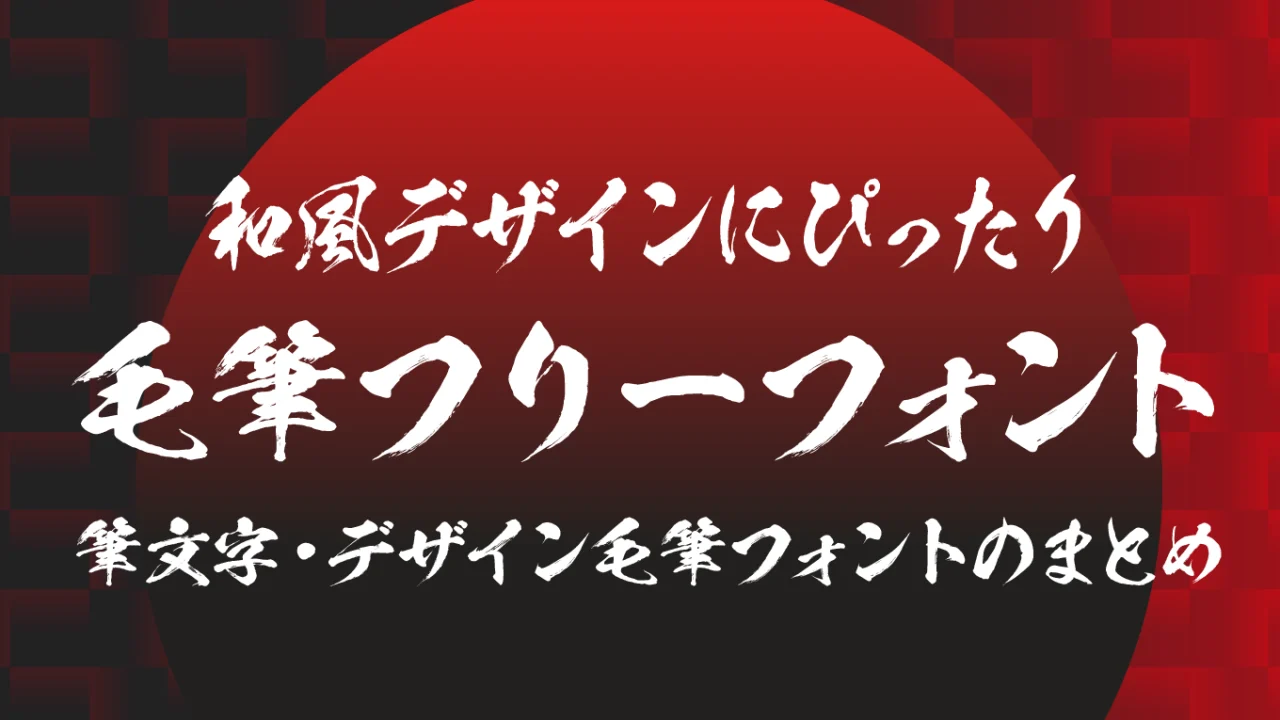
今回は、商用利用も可能な無料の毛筆フリーフォントを厳選してご紹介します。
毛筆フォントは、筆ならではの力強いハネやハライ、美しい流れによって、和風デザインにぴったりな雰囲気を演出できるフォントです。伝統的な日本らしさや風格を表現したい場面はもちろん、ロゴやタイトル、年賀状、和風イベントの告知など、さまざまなシーンで活躍します。
本記事では、そんな和の世界観を引き立ててくれる無料の日本語毛筆フォントを厳選してご紹介します。筆文字フォントカテゴリの中から、デザイン性や使いやすさに優れたフリーフォントをピックアップしましたので、ぜひお気に入りのフォントを見つけてみてください。
毛筆フリーフォントのまとめ
以下のサンプル画像は、本記事で紹介しているフォントの一部です。力強く豪快な筆文字から、繊細で上品な書風、個性的なデザイン筆文字まで、作者ごとの個性が光る魅力的な毛筆フォントを掲載しています。ぜひデザインの雰囲気や用途に合わせて、お気に入りの筆文字フォントを見つけてみてください。
玉ねぎ楷書〈激〉は、通常版よりも筆の勢いと迫力を強調した力強い毛筆フォントです。
太く大胆な線と豪快な払いが特徴で、武将の書や大きな看板を思わせる存在感があります。和の重厚感をしっかり伝えたい場面で頼もしい存在になるフォントです。
祭りや和風イベント、歴史や伝統文化をテーマにしたビジュアルなどで高い効果を発揮します。見る人の目を引く迫力あるタイトルづくりにぴったりなフォントです。
玉ねぎ楷書
玉ねぎ楷書は、毛筆の流れを残しながらも読みやすく整えられた毛筆楷書フォントです。
しっかりとした骨格がありながら、どこか素朴で温かな印象を感じさせます。伝統的な和の雰囲気を大切にしつつ、現代のデザインにも取り入れやすいバランスの良さが魅力のフォントです。
習字のお手本文字のように整っている文字なので、幅広いシーンが活躍できる筆文字です。
佑字 朴(Yuji Boku)
佑字朴は、素朴で飾りすぎない筆致が魅力の毛筆フォントです。
筆の流れを自然に残した文字には、どこか穏やかで親しみやすい空気が漂っています。格式張りすぎず、それでいて和の趣はしっかり感じられるため、日常に寄り添う和風デザインにぴったりなフォントです。
和菓子のパッケージや地域イベントの案内、観光パンフレットなどに使うと、肩肘張らない温かな和の世界観を演出できます。自然体の美しさを大切にしたい場面で活躍するフォントです。
佑字 舞(Yuji Mai)
佑字舞は、流れるような筆の動きと優雅な曲線が特徴のフォントです。
毛筆ならではの美しさを残しながらも軽やかな印象があり、上品で洗練された和の雰囲気を演出できます。和風ロゴや商品パッケージにもよく映えるフォントです。
佑字 肅(Yuji Syuku)
佑字粛は、落ち着いた筆致と端正な字形が印象的なフォントです。
派手さを抑えながらも凛とした存在感があり、格式や品格を大切にした和風デザインに適しています。旅館や和食店、伝統文化を扱うコンテンツにも使いやすいフォントです。
g_達筆(笑)
g_達筆(笑)フォントは、は、達筆な筆文字を少しユーモラスにアレンジしたような個性が光るフォントです。
大胆な筆運びや独特な線の表情が印象的で、一文字ごとに味わいがあります。遊び心と和の風情を同時に表現できるため、見る人の記憶に残りやすいフォントです。
桜鯰(おうねん)フォント
桜鯰は、筆の勢いや墨のかすれを大胆に取り入れた個性的な毛筆フォントです。
文字の輪郭に力強い動きがあり、一文字ごとに躍動感を感じられます。豪快さと遊び心が同居しており、見る人の印象にしっかり残る存在感があるフォントです。
祭りや和風イベント、歴史をテーマにした作品などとの相性が良く、活気のある和の雰囲気を演出できます。力強く印象的なタイトルを作りたい場面にぴったりなフォントです。
青柳隷書しも
青柳隷書しもは、隷書の落ち着いた品格と筆文字ならではの自然な揺らぎをあわせ持つ毛筆フォントです。
和菓子のパッケージや旅館の案内、季節感を伝えるビジュアルなどと相性が良く、上品で親しみやすい和風デザインを演出できます。四季や自然を題材にした作品にもぴったりなフォントです。
藍原筆文字隷書
藍原筆文字隷書は、筆で丁寧に書き上げたような自然な線の流れが魅力のフォントです。
整った隷書ベースの読みやすさを持ちながら、手書きならではの温もりもしっかり感じられます。派手な装飾に頼らず、和の美しさを素直に表現できるフォントです。
和風サイトや観光案内、商品説明など幅広い場面で使いやすく、落ち着いた信頼感のあるデザインに仕上がります。伝統的な和の雰囲気を自然に取り入れたいときにおすすめのフォントです。
永山楷(Nagayama Kai)
永山楷は、楷書らしい端正な骨格と筆文字の味わいをあわせ持つフォントです。
整った字形で読みやすく、落ち着きや信頼感を自然に伝えてくれます。格式ある和風デザインから案内文まで幅広く使いやすい、汎用性の高いフォントです。
しょかき ささぶね
しょかきささふねは、やわらかな筆致と素朴な表情が魅力のフォントです。
自然な揺らぎを残した文字は、人の手で丁寧に書かれたような温かみを感じさせます。和雑貨や季節の挨拶、和風カフェのデザインなどにぴったりなフォントです。
作者さまいわく「笹の葉のような筆画と、流れるようなイメージから「ささぶね」と命名しました」とのこと。
しょかきうたげ
しょかきたげは、墨のかすれや筆圧の変化を活かした力強いフォントです。
勢いのある線が印象的で、和風デザインに活気と迫力を与えてくれます。祭りやイベント告知など、目を引くタイトル表現をしたいときに活躍するフォントです。
居酒屋のメニューに「本当にありそう」な文字がとてもステキです。
衡山毛筆フォント
衡山毛筆フォントは、鋭い払いと力強い筆勢が魅力のフォントです。
文字の一画ごとに躍動感があり、伝統的な書道作品のような風格を感じさせます。和風ポスターやタイトルなどで存在感を発揮し、重厚な世界観を演出できるフォントです。
なんと14000字もの手書き文字をスキャンして作られているので、細部までのリアルな毛筆がとっても美しくカッコイイ毛筆フォントです。
しょかきさらり
しょかきさらりは、細く軽やかな筆運びが印象的なフォントです。
さらさらと筆を走らせたような自然な線が美しく、和紙に書かれた短冊や手紙のような風情を感じさせます。静かで上品な和の空気を演出したいデザインにおすすめのフォントです。
年賀などのご挨拶で自分で字で書けたらかっこいいなぁと憧れるようなとっても素敵な字です。
アームドバナナ
アームドバナナは、自由奔放な筆の動きを活かしたユニークな毛筆フォントです。
少し遊び心のある字形が特徴で、堅苦しい和風ではなく親しみやすい和の表現に向いています。イベントや個人作品など、楽しい雰囲気を演出したい場面にぴったりなフォントです。
TA霜林筆02
TA霜林筆フォントは、行書体をベースにして作られているため、習字のお手本のような美しくデザイン毛筆フォントです。
TA風雅筆01
TA風雅筆フォントは、楷書体をベースにして作られているため、美しく力強いデザイン毛筆フォントです。
TA筆ばらい
TA筆ばらいフォントは、少し崩しさ可愛さがある筆文字フォントです。
TA寒椿
TA寒椿フォントは、上半身に重心があるような独特なバランスな風合いがあるデザイン筆文字フォントです。